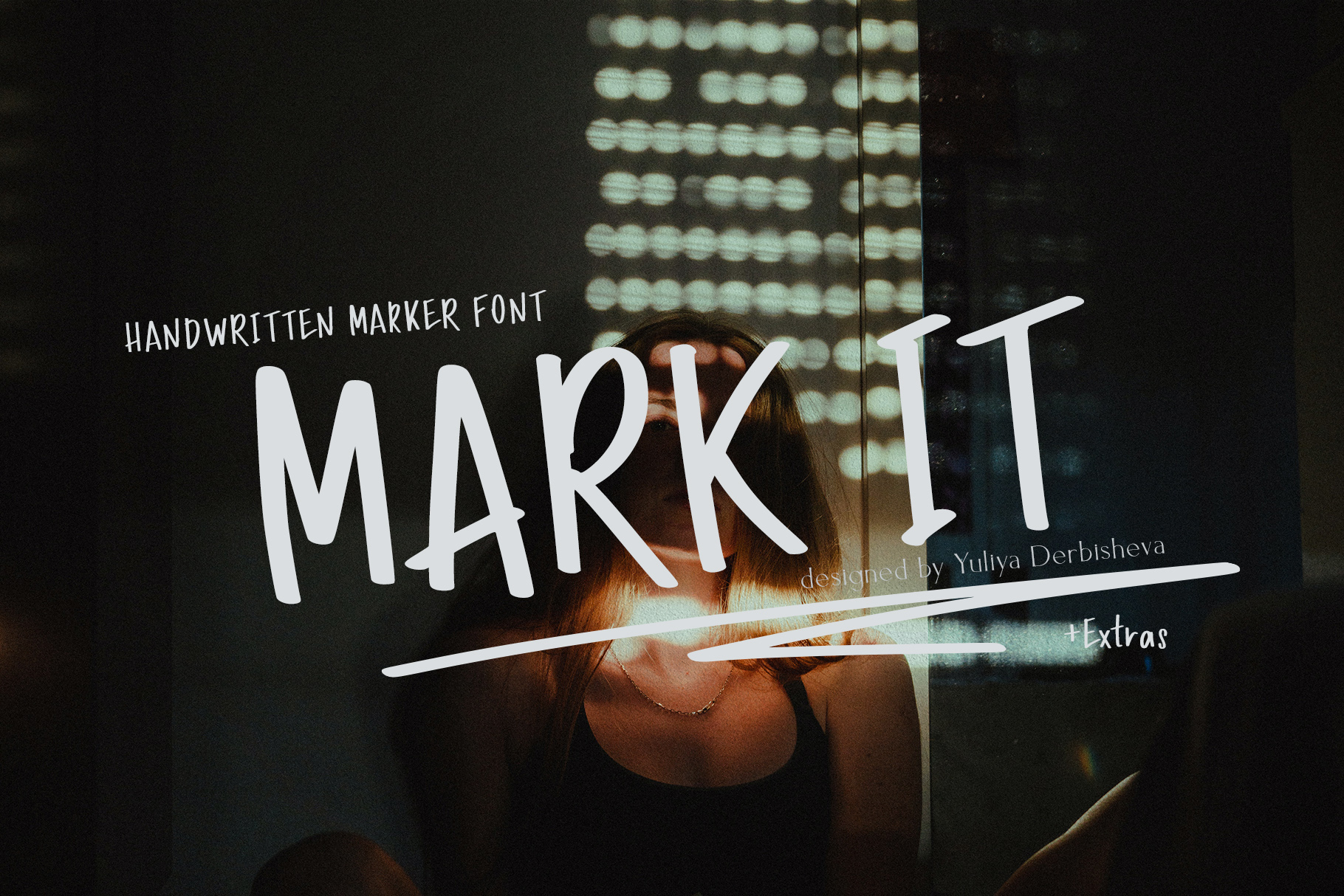
Каракули декоративный нацарапанный шрифт кириллица русские шрифты
Этот акцентный декоративный шрифт идеально подходит для создания задорных заголовков, эмоциональных надписей и дерзкого визуального контента. Несмотря на свой бунтарский характер, комплект содержит как прописные, так и строчные буквы, что обеспечивает отличную читаемость.
Вместе со шрифтом вы получаете 54 авторские векторные дудл-иллюстрации: нарисованные от руки линии, стрелки, подчеркивания, рамки, смайлы, короны и галочки. Они идеально дополняют шрифт и позволяют за пару минут собрать готовый креативный макет.
Сферы применения шрифта «Каракули»:
Социальные сети и медиа: яркие обложки, рилс/сторис, баннеры для Telegram-каналов, VK, Pinterest, мем-контент, оформления YouTube-превью и блогерских проектов.
Айдентика и брендинг: логотипы для уличных брендов одежды, локальных кофеен, скейт-шопов, молодежных фестивалей, крафтовых баров и творческих студий.
Упаковка товаров: этикетки для напитков, снеков, соусов, крафтового пива, парфюмерии и мерча ручной работы.
Печатная реклама и полиграфия: плакаты, постеры, афиши концертов и вечеринок, стикерпаки, открытки, обложки альбомов и книг.
Маркетплейсы: трендовая инфографика и обложки карточек товаров на Wildberries и Ozon в категориях «Молодежная одежда», «Канцелярия», «Подарки» и «А аксессуары».
Главные особенности шрифта:
Полная поддержка кириллицы (русский язык) и латиницы.
Выраженная чернильная текстура и гранж-эффект в каждом символе.
54 дудл-иллюстрации (линии, короны, рамки, значки) для оформления.
Поддерживаемые языки:
Шрифт мультиязычен и включает кириллицу (русский язык), а также европейские языки: английский, французский, немецкий, итальянский, испанский, портуальский, датский, норвежский, шведский, финский, эстонский, турецкий и языки романской группы.